Шрифты и иконки — два важных компонента интерфейса. Важно, чтобы они не конфликтовали, а дополняли и усиливали друг друга. Как же составить такую пару правильно?
Гармоничное сочетание иконок и шрифта — важное условие для достижения визуальной последовательности. Так все элементы дизайна будут работать вместе, создавая узнаваемый бренд и улучшая опыт взаимодействия.
Отправная точка
Выбирая иконки в пару к шрифту, учитывайте следующие факторы:
- Цель и контекст. Кто ваша аудитория? Какое сообщение вы хотите донести? Каким будет общий тон проекта? И шрифт, и иконки должны соответствовать этим идеям.
- Стиль и эстетика. Оцените визуальный стиль проекта, ищите шрифты и иконки, которые вписываются в эту эстетику.
- Масштабируемость и адаптивность. Оцените масштаб проекта и контекст, к которому должны будут адаптироваться иконки. Вам могут понадобиться значки, выполненные в нескольких стилях или даже в разных начертаниях (имеется в виду разная толщина обводки).
Вот небольшое руководство по выбору правильных иконок, основанное на стандартной классификации шрифтов и их анатомии.
Шрифты без засечек
Шрифты без засечек выглядят лаконично и аккуратно. Их часто используют в цифровых интерфейсах и в графическом дизайне.
С такими шрифтами сочетаются чистые, простые, современные иконки, в основе которых лежат минималистичные разборчивые формы.
Пример: набор иконок Ultimate. Он включает огромное количество нейтральных значков в разных стилях (Light, Regular, Bold, Duotone и Colors) — все они идеально сочетаются с гротесками.
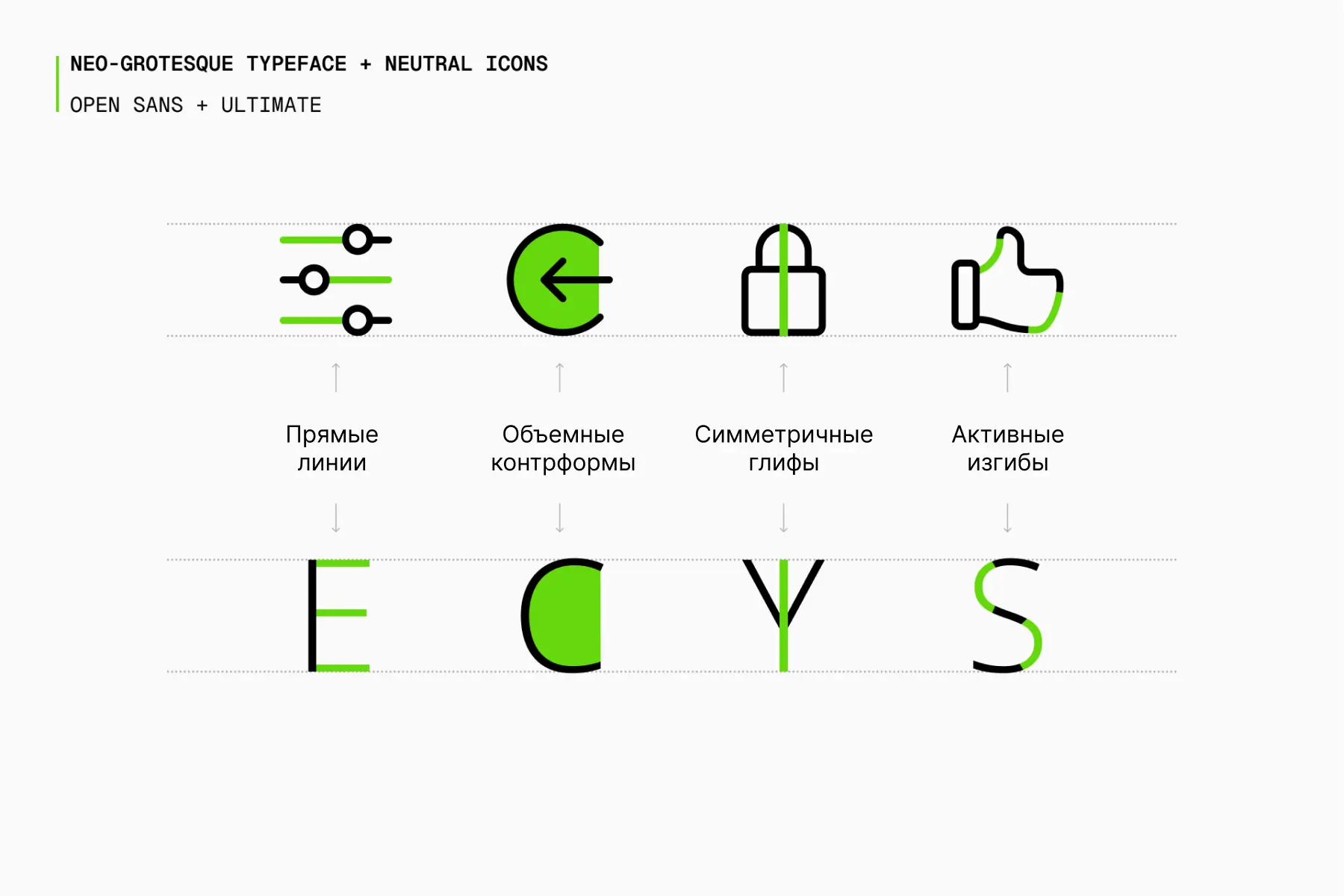
Отличная комбинация — иконки Ultimate и Open Sans, гуманистический гротеск с объемными контрформами, который отличается высокой читабельностью. Альтернативные варианты: Noto, Lato, Gill Sans.
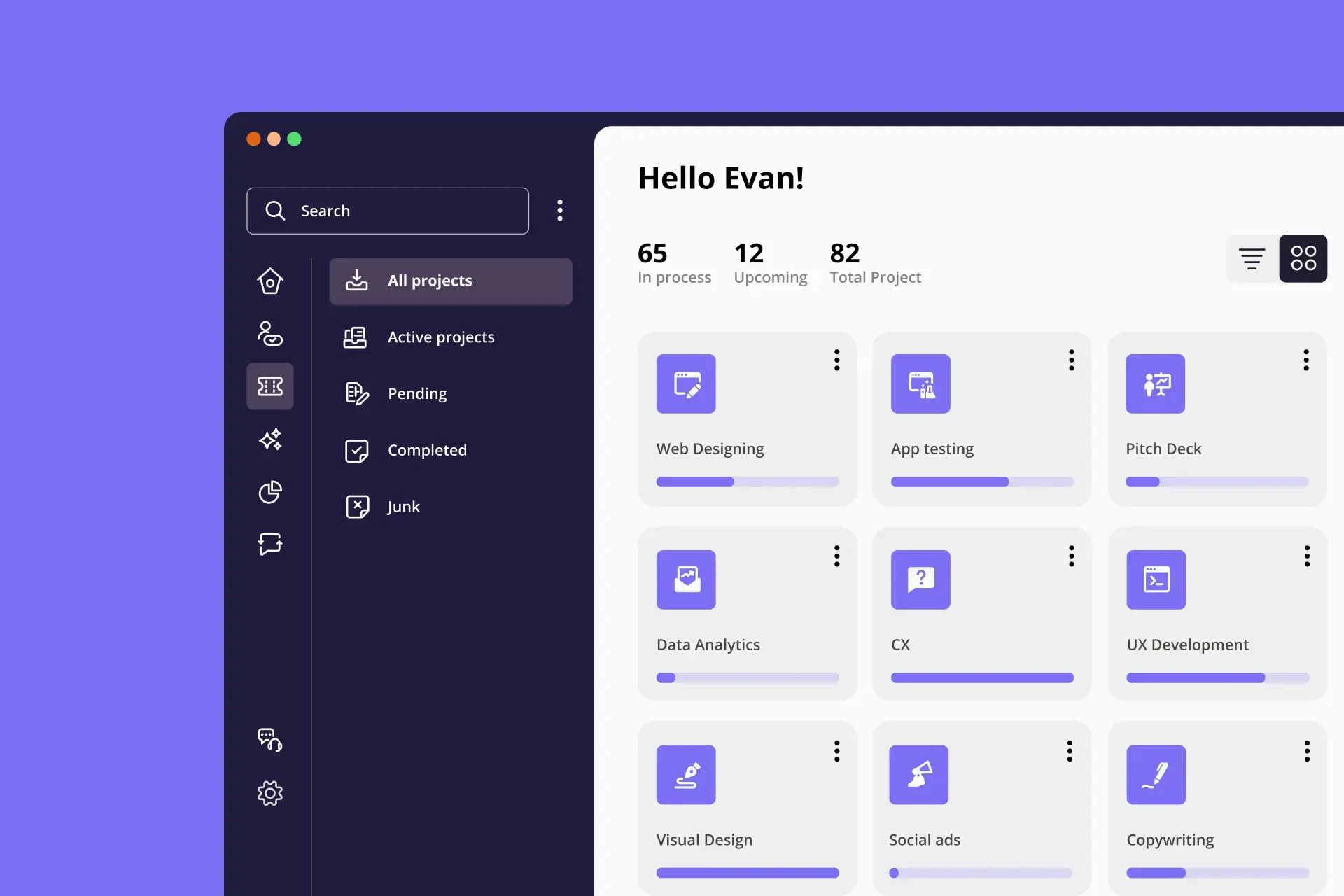
Другой похожий набор иконок — Core. Значки представлены в четырех стилях (Line, Solid, Duo и Flat), они кажутся еще более простыми и универсальными. Благодаря своей впечатляющей адаптивности такие иконки идеально сочетаются со шрифтами без засечек.
Иконки Core отлично смотрятся в комбинации с Work Sans, шрифтом, который был создан на основе ранних гротесков и имеет 10 начертаний, что обеспечивает максимальную гибкость. Если этот шрифт вам не по вкусу, вы также можете присмотреться к Inter, Roboto или Neue Haas Grotesk.
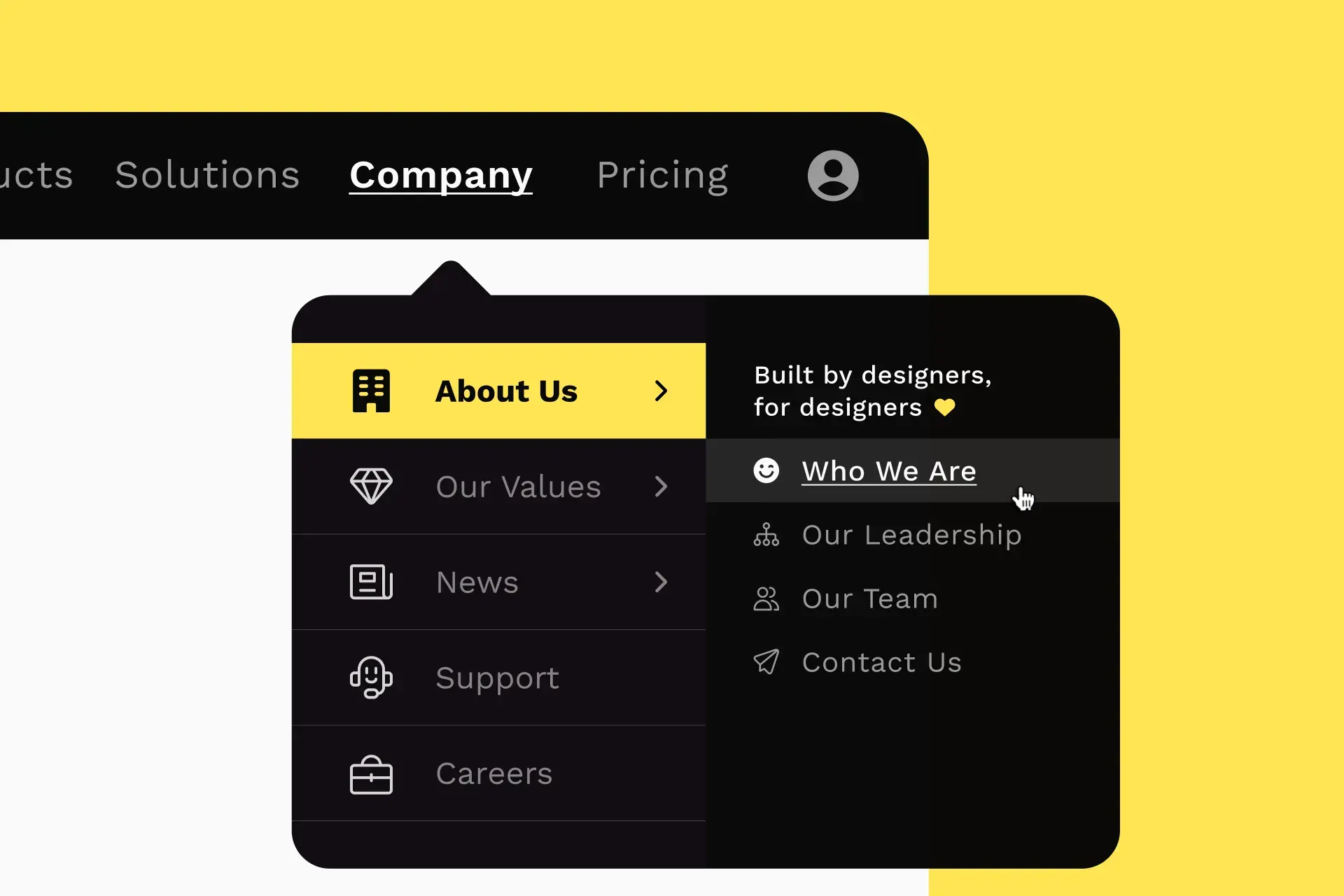
Однако если вам нужен набор иконок, который будет работать в самом маленьком масштабе, обратите внимание на Micro. Он имеет те же базовые характеристики, что и Core, но построен на основе более мелкой сетки и, следовательно, отличается меньшим уровнем детализации и повышенной разборчивостью.
В этом случае отличной парой будет более геометричный шрифт с широкими буквами, такой как Montserrat. Альтернативные варианты: Poppins, Raleway или Gotham.
Ищете что-то более яркое и характерное? Ваш выбор — Flex. Эти «живые», размашистые, элегантные иконки никого не оставят равнодушным. Чтобы создать гармоничную пару, используйте шрифт со скругленными концами штрихов и большим количеством кривых.
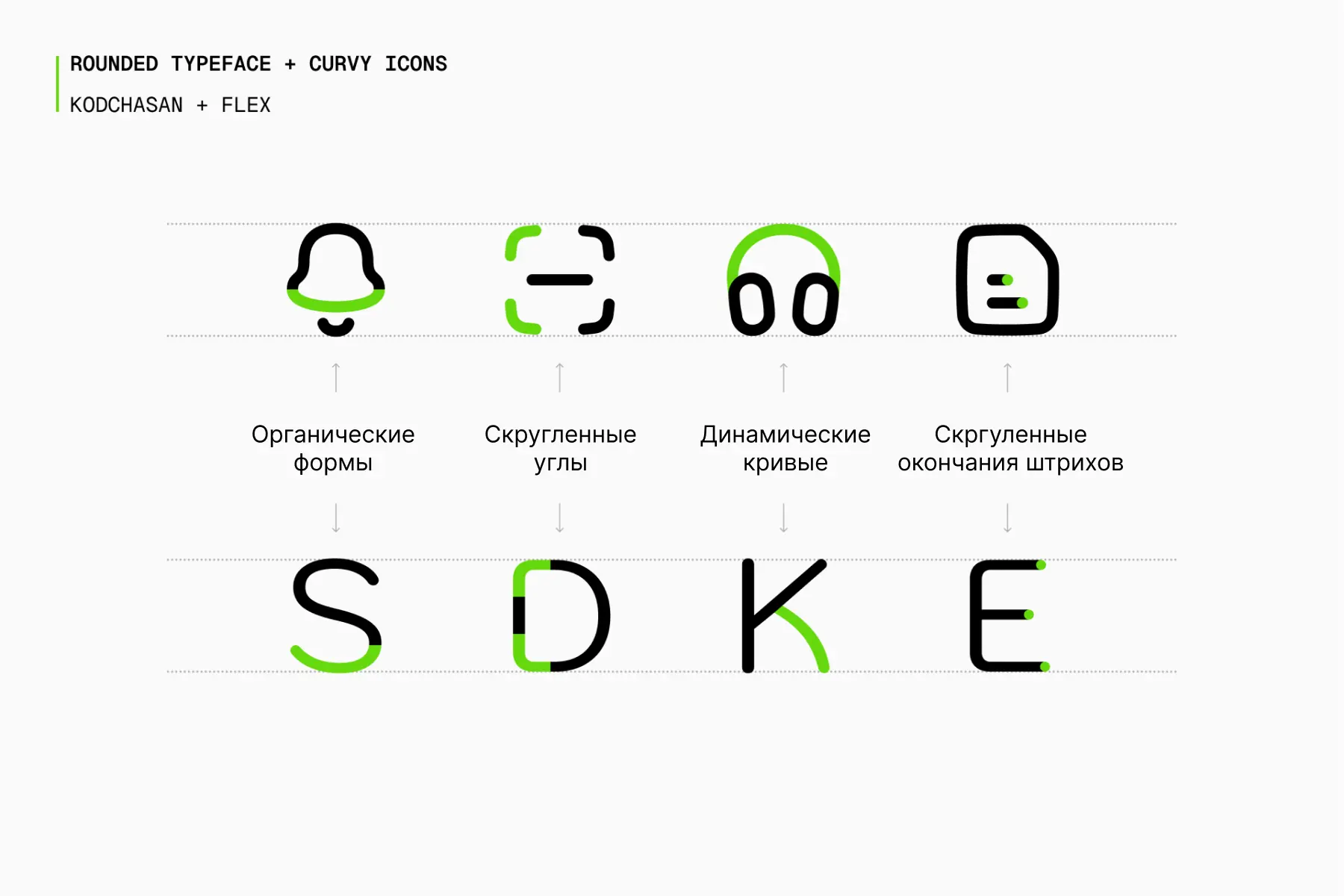
Шрифт Kodchasan — удивительно подходящий партнер для Flex. Такое ощущение, будто они были построены на основе одних и тех же принципов. Есть и более нейтральные альтернативы: Rubik, Nunito, Noway Round.
Если же вам нравятся более строгие, «архитектурные» гротески, отличным вариантом будет Sharp. Иконки из этого набора выглядят геометричными и грубоватыми.
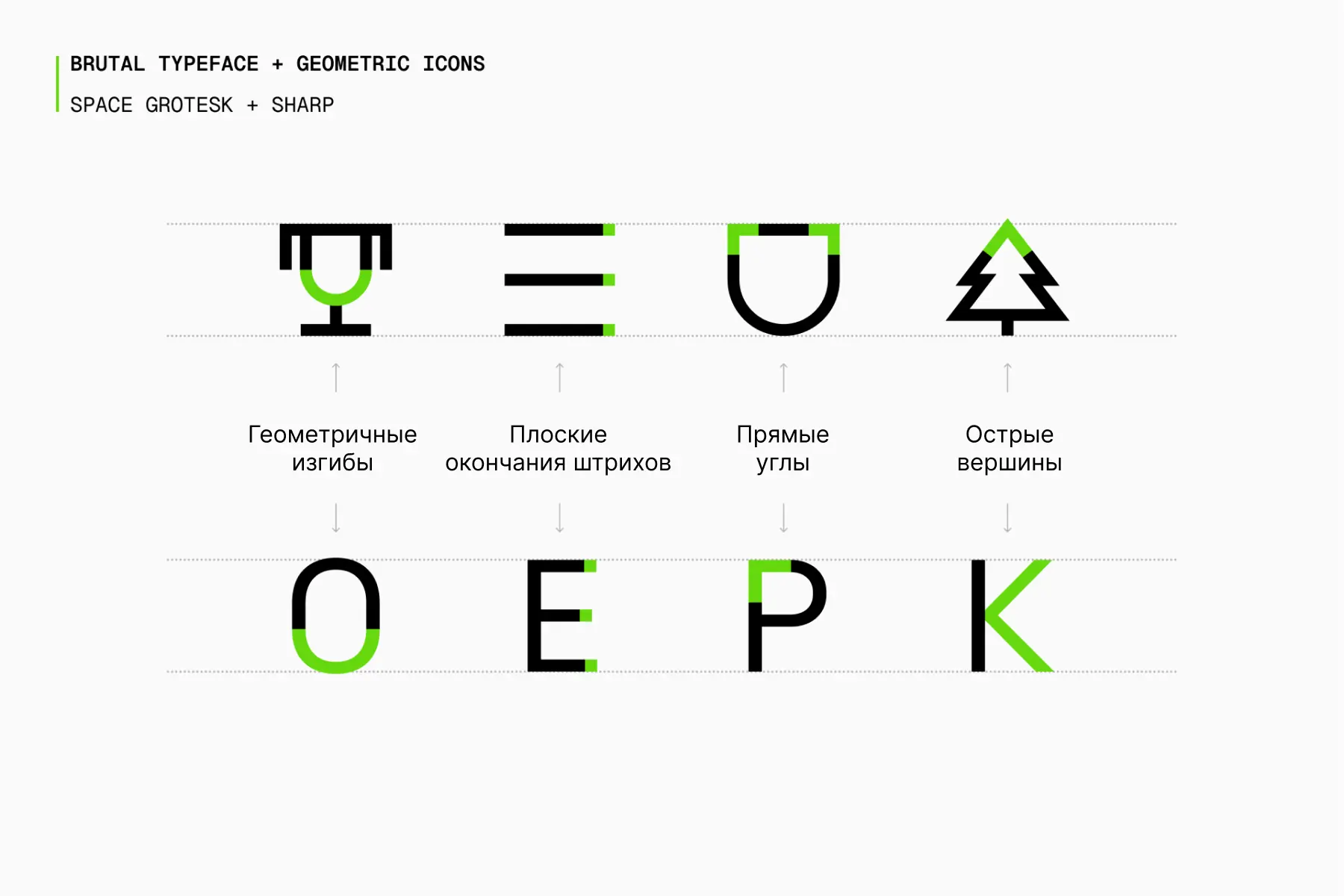
Такому брутальному набору иконок нужен брутальный шрифт, например, Space Grotesk — уникальный, но при этом разборчивый гротеск в стиле хай-тек. Другие варианты: DM Sans, Archivo, Neue Machina.
Шрифты с засечками
Шрифты с засечками выглядят более формально и традиционно. Их часто можно встретить в книгах, газетах и журналах.
С такими шрифтами сочетаются элегантные иконки с изысканными деталями и умеренным контрастом.
Хорошее решение — уже рассмотренные наборы Ultimate и Core. Они достаточно универсальны и не будут отвлекать слишком много внимания от основного контента.
В случае с Ultimate для создания «традиционного» визуала подойдет антиква старого стиля, например, EB Garamond. Альтернативные варианты: Cormorant, Cardo, Sabon.
Что касается Core, то с ним лучше всего будет смотреться переходная антиква (сочетающая в себе признаки антикв старого и нового стиля), например, Merriweather, с ее более высоким контрастом и симметричными глифами. Такая комбинация, несмотря на свою серьезность, будет выглядеть достаточно современно. Другие возможные варианты — Domine, Spectral или Signifier.
Однако существуют наборы иконок, которые изначально были задуманы для использования в паре с антиквами. Например, Platinum был разработан специально для люксовых брендов. Его отличают тонкие штрихи, вогнутые кривые и острые углы, которые придают ему элегантный и классический вид.
Platinum — более универсальный набор иконок, чем может показаться на первый взгляд. Контрастные шрифты с засечками, такие как Boska, идеально сочетаются с ним благодаря присущей им утонченности. Если вам нравится этот стиль, также обратите внимание на Prata, Marcellus и Domaine.
Итак, шрифты и иконки — часть единого визуального языка. Они строятся на основе похожих принципов и необходимы для создания целостного гармоничного дизайна. Внимательно анализируйте основные характеристики этих элементов, и вы сможете создавать впечатляющие сочетания, неподвластные времени.